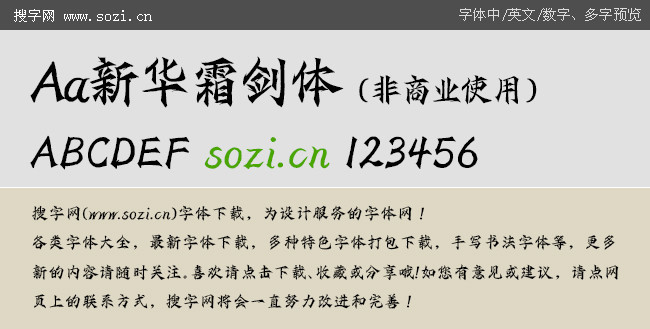
Aa新華霜劍體
搜字網(wǎng)給大家提供一款A(yù)a新華霜劍體(非商業(yè)使用)中文字體下載,該字體是一款非常漂亮的手寫書法字體,風(fēng)格比瀟灑大方,字跡鋒芒畢露,具有很好的視覺感,適用于平面宣傳設(shè)計(jì)、網(wǎng)頁設(shè)計(jì)、海報(bào)設(shè)計(jì)等應(yīng)用(此字體為個人非商用版,商用可以聯(lián)系QQ:1006760504)。